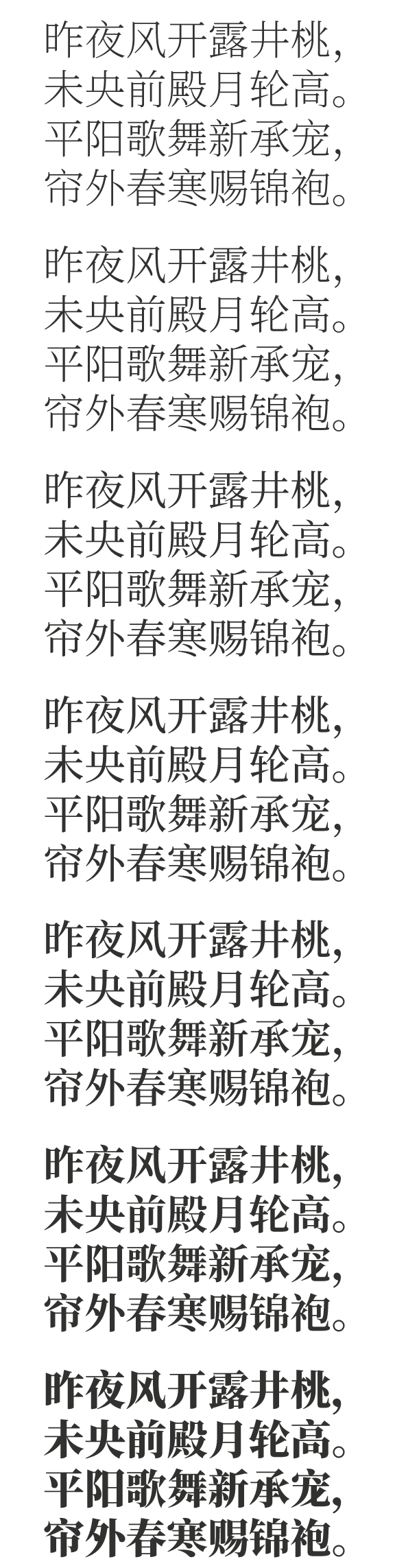
繼思源黑體之后, Adobe與谷歌又一款開源泛中日韓字體——思源宋體于今天4月4日正式發(fā)布。
思源宋體是 Adobe Type 發(fā)布的最新泛 CJK 字體,它是對應于思源黑體的宋體字體;我們發(fā)布這兩種字體是為了響應統(tǒng)一設計的需求,以服務于東亞 15 億人口。
思源宋體支持四種不同的東亞語言(簡體中文、繁體中文、日語和朝鮮語),7 種粗細類型中的每一種都有 65,535 個字形,可共同呈現(xiàn)一致的視覺美感。該字體還包含多個西方字形,支持拉丁語、希臘語和西里爾文腳本,這些字形均來源于 Source Serif。